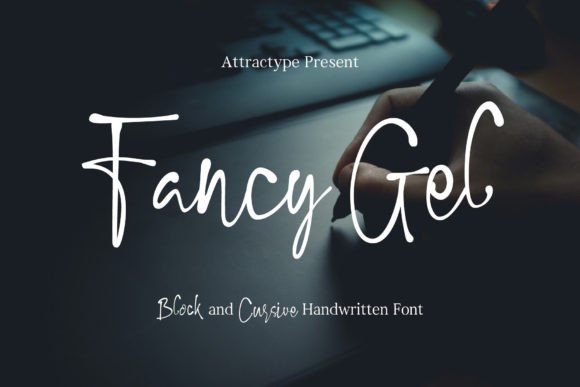
Fancy Gel
Fancy Gel – A Fonte Manuscrita que Transforma Seu Design
Se você procura uma tipografia que una versatilidade, elegância e legibilidade, a Fancy Gel chega como a solução perfeita. Desenvolvida com traços que alternam entre estilo bloco e cursivo, essa fonte se destaca em diversos contextos, desde títulos impactantes até assinaturas sofisticadas.
Por que Fancy Gel é a escolha ideal?
- Design híbrido: combina o peso visual dos caracteres em bloco com a fluidez dos detalhes cursivos, oferecendo um visual dinâmico sem perder clareza.
- Legibilidade impecável: mesmo em tamanhos menores, as letras permanecem nítidas, o que a torna ótima para rótulos e etiquetas.
- Luxo para marcas: o toque refinado da fonte confere sofisticação a logotipos, embalagens e materiais de branding.
- Versatilidade de uso: ideal para títulos, citações inspiradoras, marcas d'água e, claro, assinaturas personalizadas.
Aplicações práticas da Fancy Gel
Veja como a Fancy Gel pode elevar o nível dos seus projetos:
- Títulos de capa: crie manchetes que capturam a atenção instantaneamente.
- Citações motivacionais: dê um ar de autenticidade e elegância às frases que você quer destacar.
- Rótulos de produtos: garanta que informações essenciais sejam lidas rapidamente, sem perder o charme visual.
- Identidade visual de marcas premium: use a fonte em logotipos, cartões de visita e embalagens para transmitir exclusividade.
- Assinaturas digitais: personalize e-mails ou documentos com um toque profissional e único.
Conclusão – Vale a pena investir na Fancy Gel?
Em resumo, a Fancy Gel entrega tudo que designers e empreendedores buscam: um visual sofisticado, alta legibilidade e flexibilidade para múltiplas aplicações. Seja para projetos corporativos de alto padrão ou para criações pessoais que exigem um toque artesanal, esta fonte manuscrita garante resultados impressionantes e profissionais.